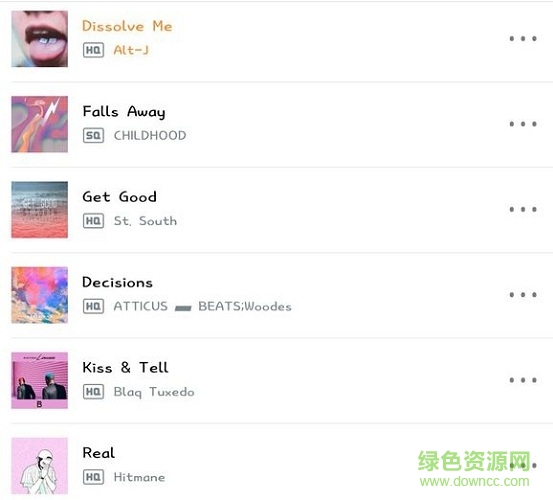
柚子體是淺淺推出的一款非常清秀純粹的手寫字體,英文干凈清晰,中文娟秀活潑,十分宜人,讓你的藝術(shù)設(shè)計(jì)更有獨(dú)特魅力,喜歡的朋友就來綠色資源網(wǎng)體驗(yàn)吧!
柚子體字跡清晰明麗,是新浪博主淺淺@SuriiiMeow自制的柚子體,中文端正,有著繁體字體和板報字體的特色體驗(yàn),英文正直,結(jié)構(gòu)上也比較鮮明,是一款非常有趣的手機(jī)字體,適用范圍較廣。